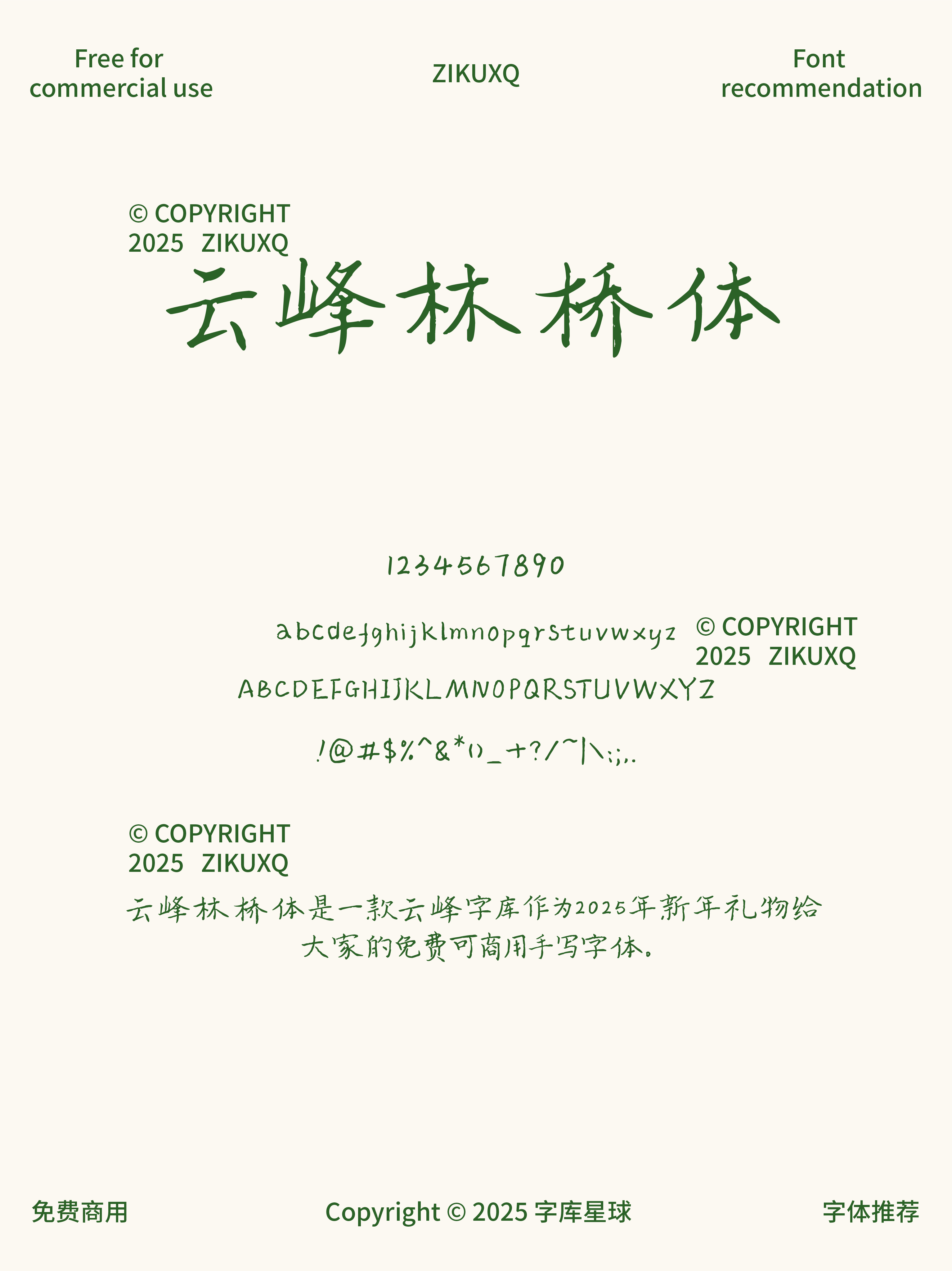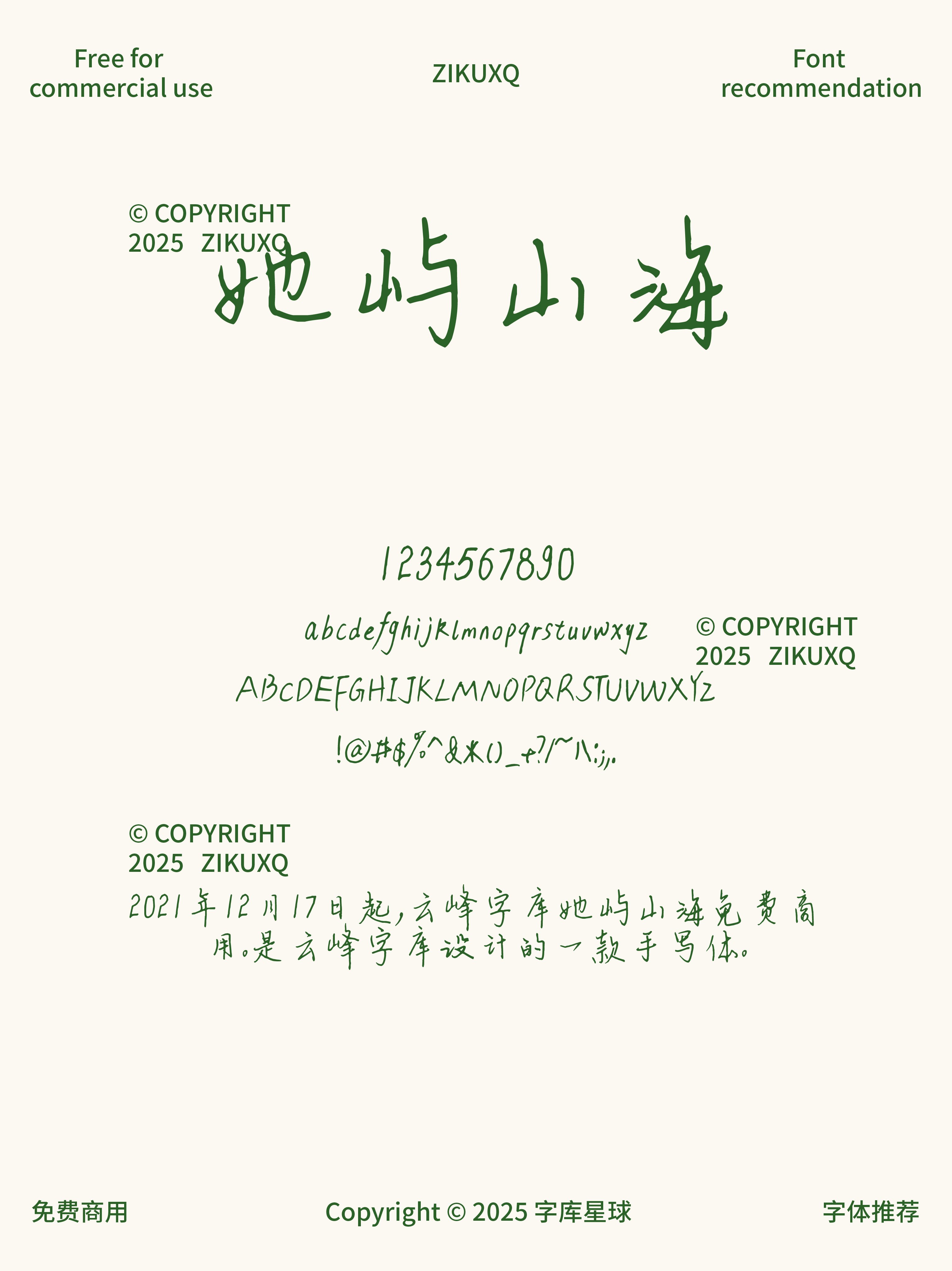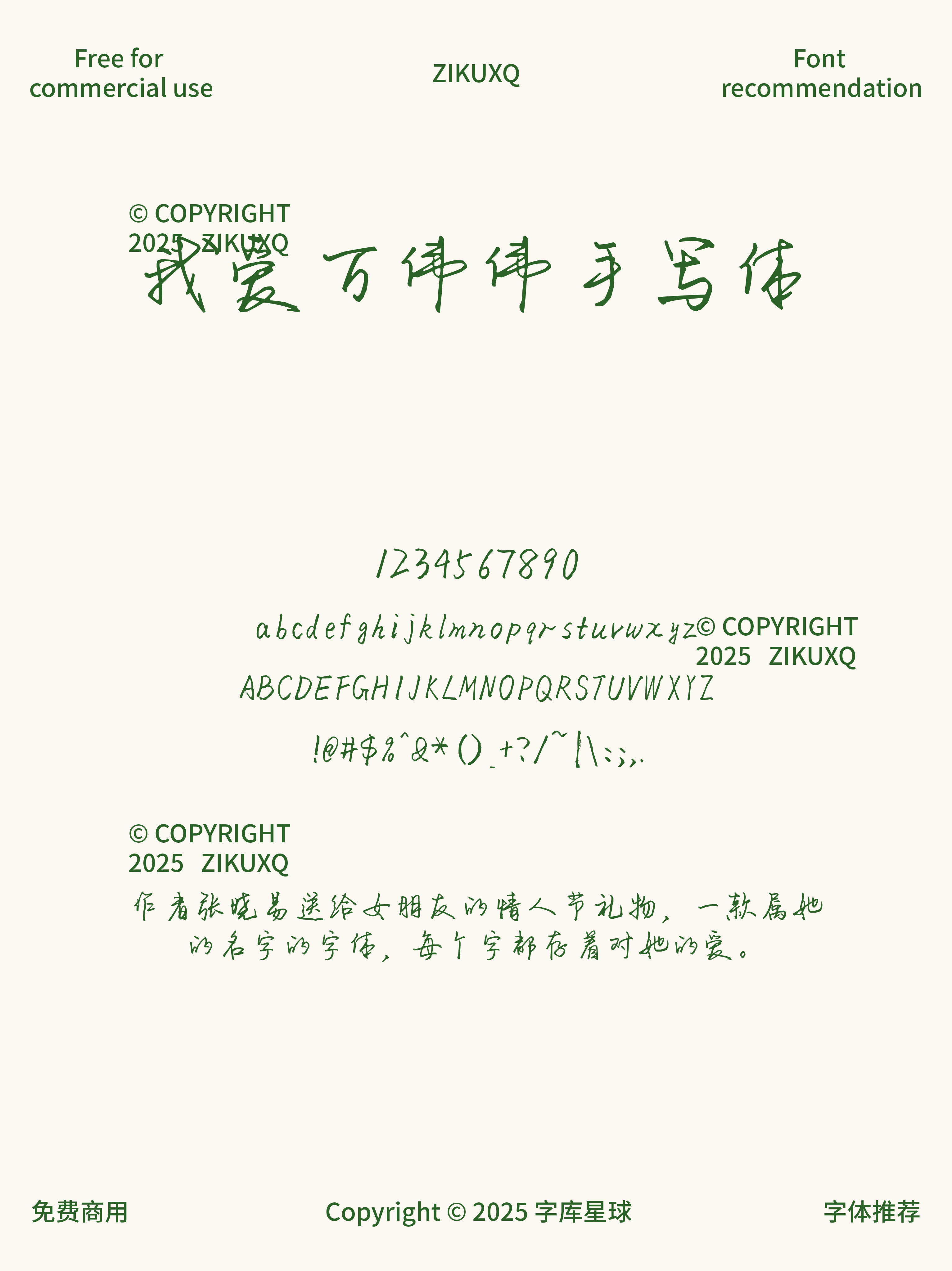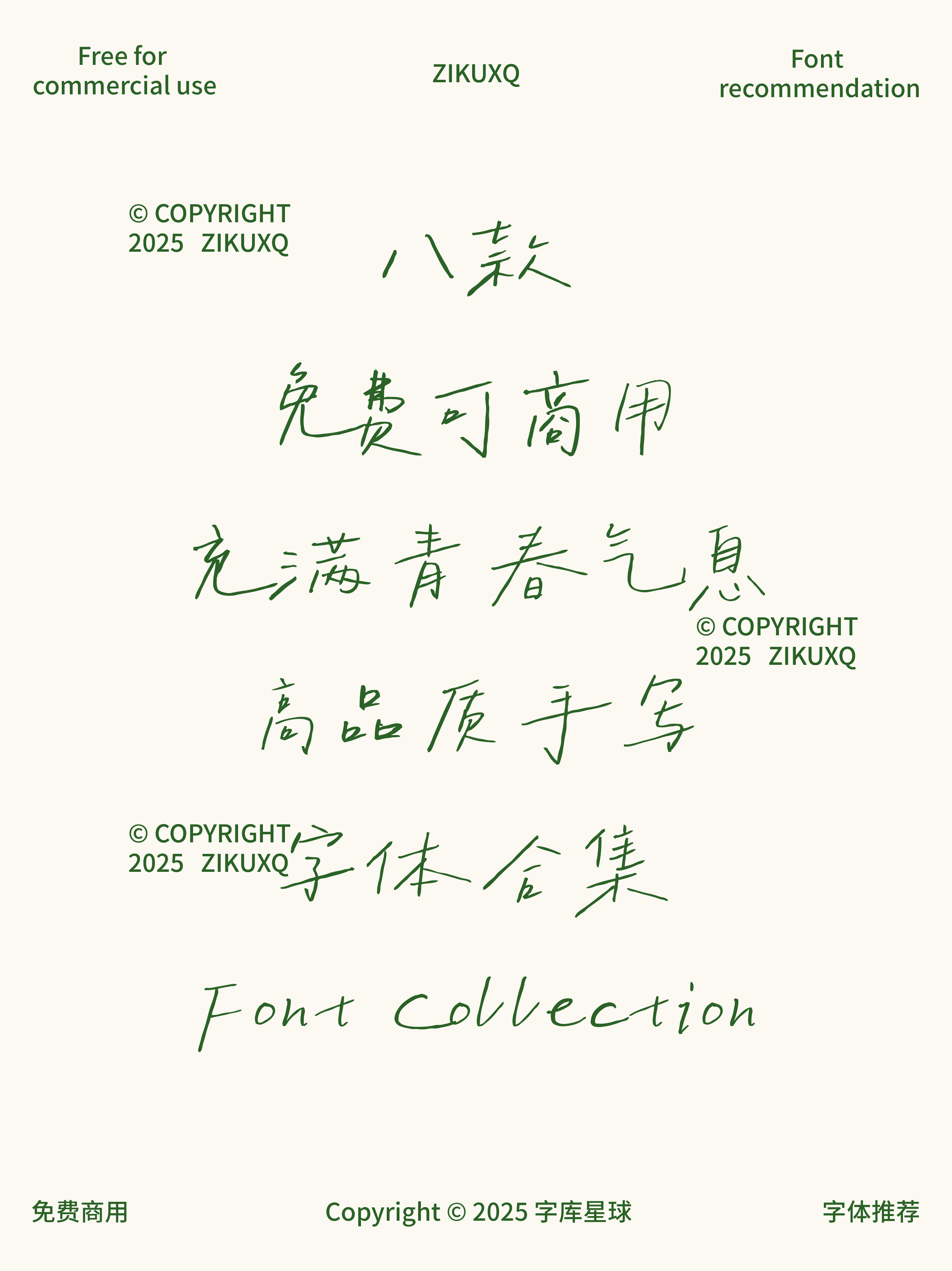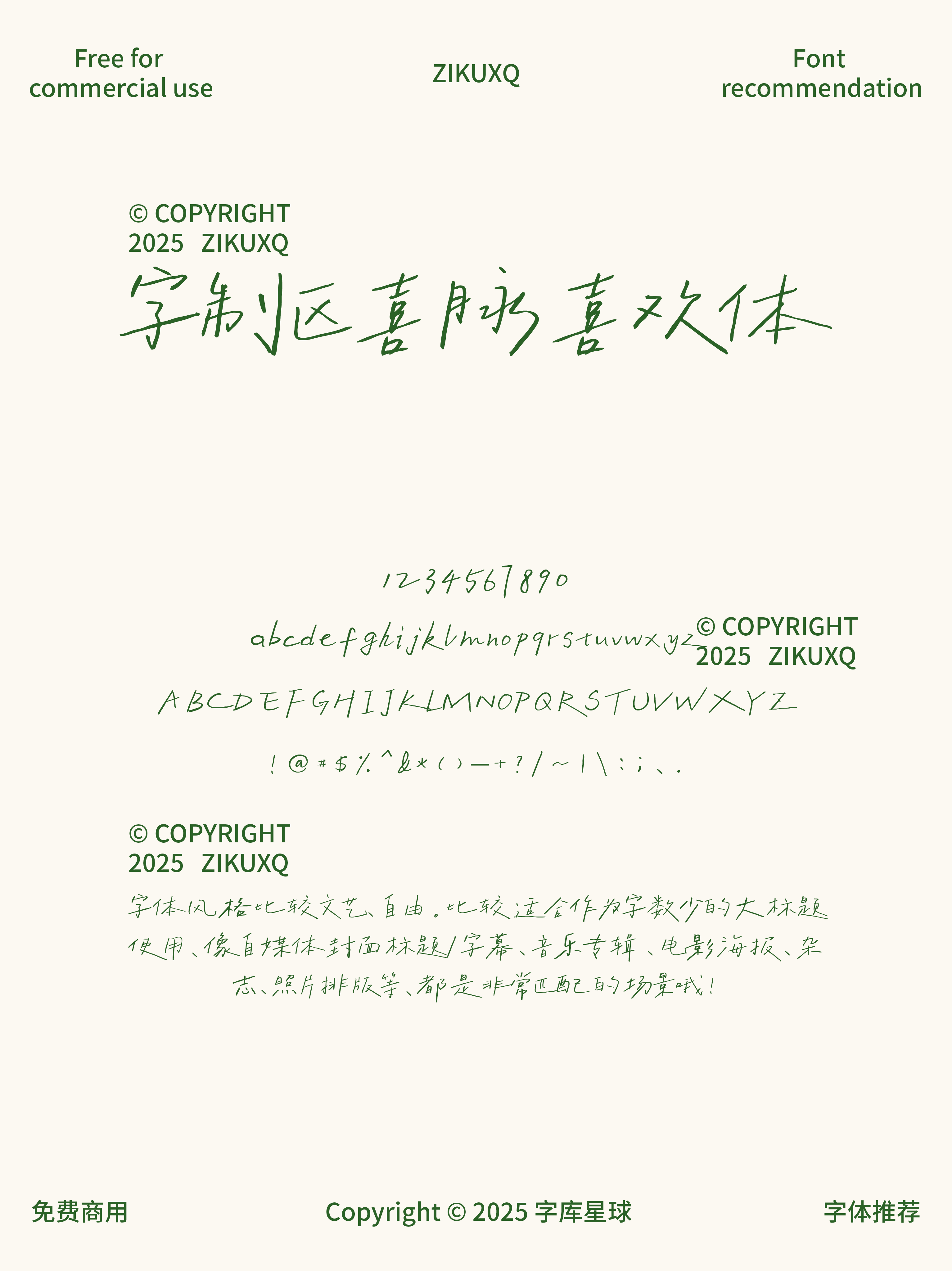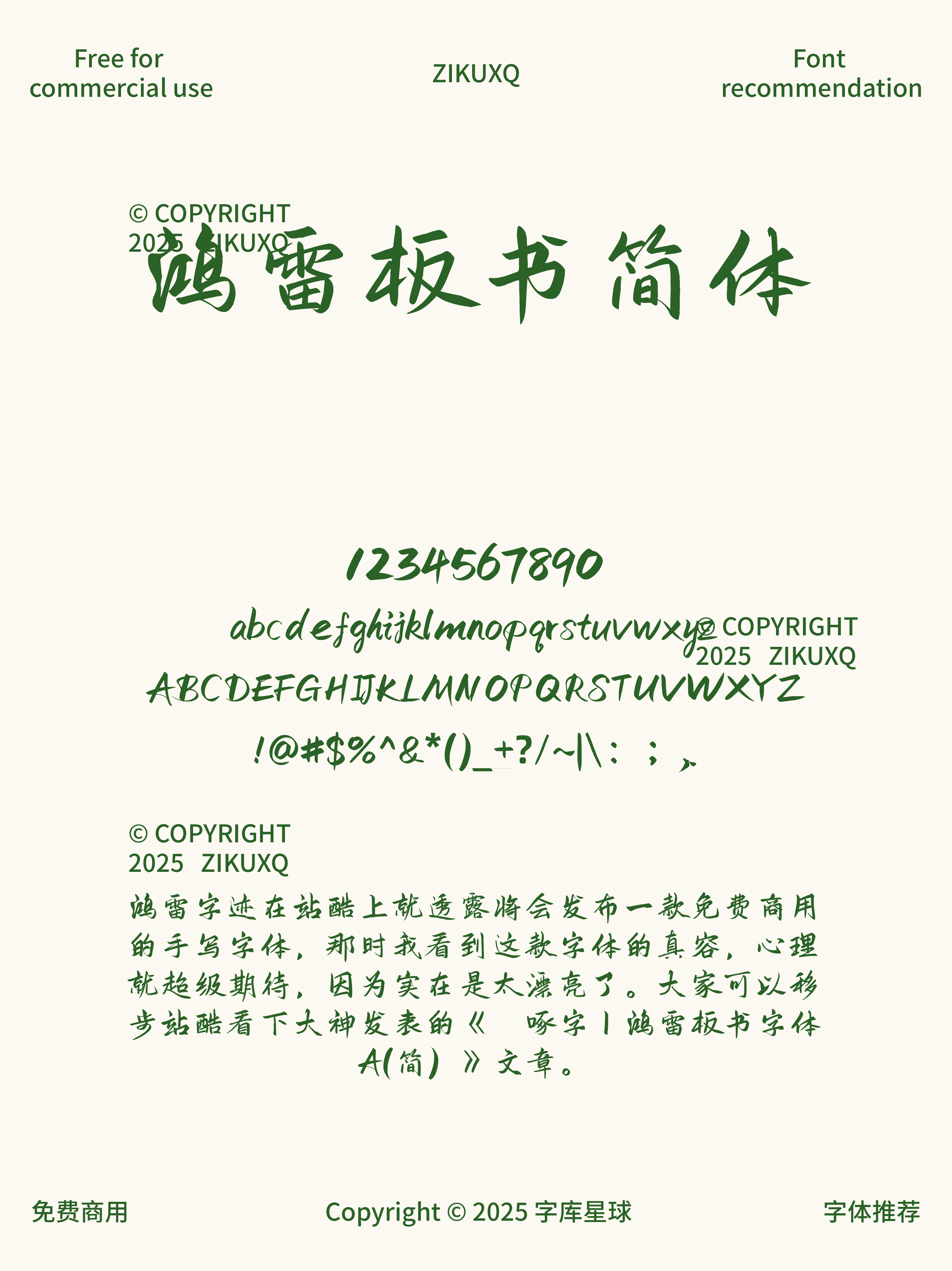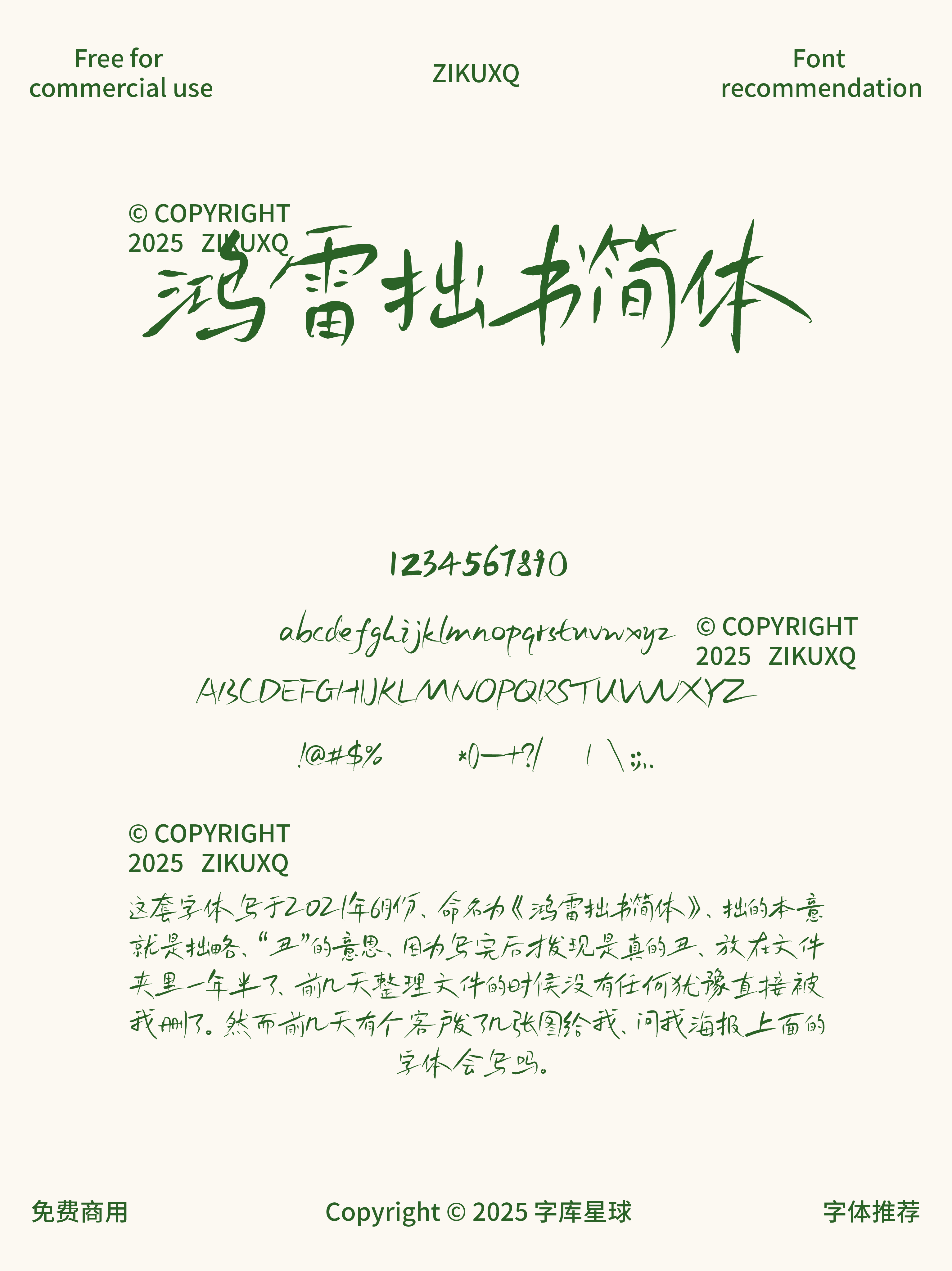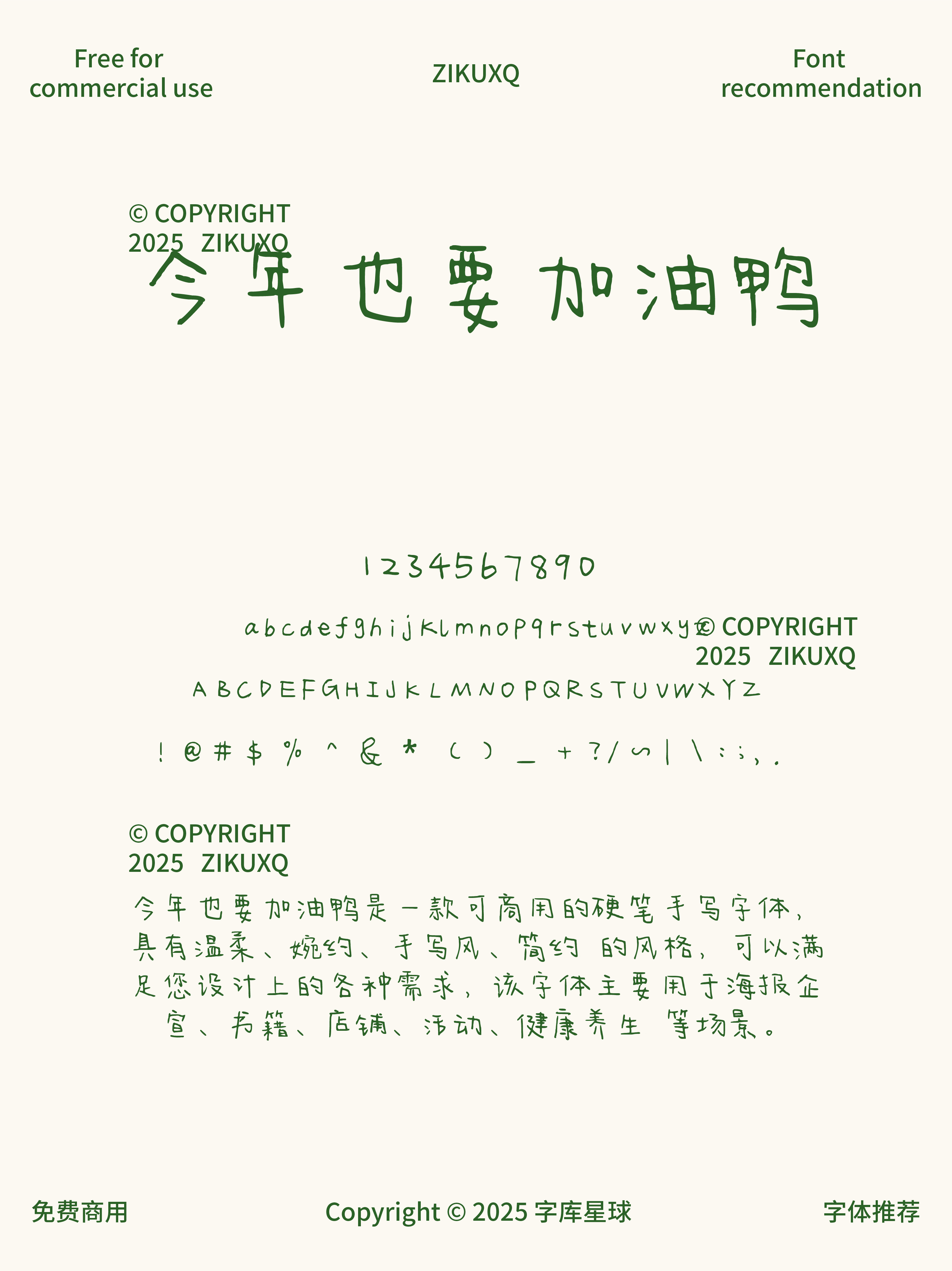
八款免费可商用充满青春气息高品质手写字体
今天给大家分享 8 款充满青春气息的免费可商用手写字体,让你的设计瞬间活力满满!
文艺感爆棚,笔画流畅自然,每一笔都像在诉说青春故事。字符库超全,6796 个字符,从数字到标点,满足各种创作需求。不管是手账记录还是社交媒体配图,都能完美适配,让你的文字自带滤镜,格调飙升。
活泼俏皮,充满童趣,看到它就像回到了无忧无虑的校园时光。笔画结构和粗细都很灵活,轻松营造出欢乐氛围。特别适合用在网页标题、促销主题、产品包装等场景,让你的设计瞬间抓住眼球,活力四射。